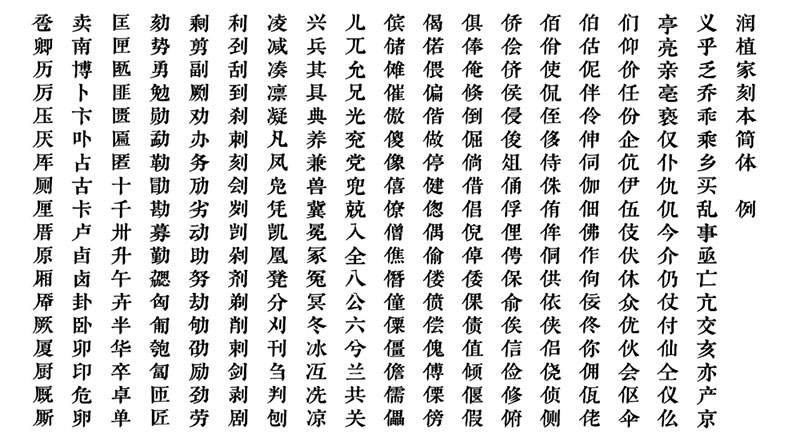
此前,润植家曾发布世界首个首个昆曲专用工尺谱编写的免费公益字体:“润植家工尺谱字体”。也发布过世界首个免费公益昆曲简谱输入字体,可用于昆曲(及音乐简单的剧种)的简谱编写,上月,我们发布的润植家康熙字典美化体(常规款和清瘦款),收到广泛关注和好评。并且,在大约半个月间,这款字体进行了大量升级,进一步美化更新和扩充了一百多个字(为更好的使用效果,强烈建议各位使用者更新到最新版哦)。
不过,这两款字体,是繁体的,更偏向用于传统书籍。因此,对于现代出版和平面设计的需求,也有用户提出:有没有类和润植家康熙字典美化体风格相似,但是,用于简体场景,最好是宋体风格的古刻本风格字体呢?
为解决这个需求,我们又推出一款重磅的刻本字体:润植家刻本简体
和润植家康熙字典美化体相似,这款字体,也是源自刻本风格,但是更加圆润,在刀篆风格上,加上了一点毛笔书写的风格,看起舒服养眼。横排纵排,标题和正文,都可以适用。